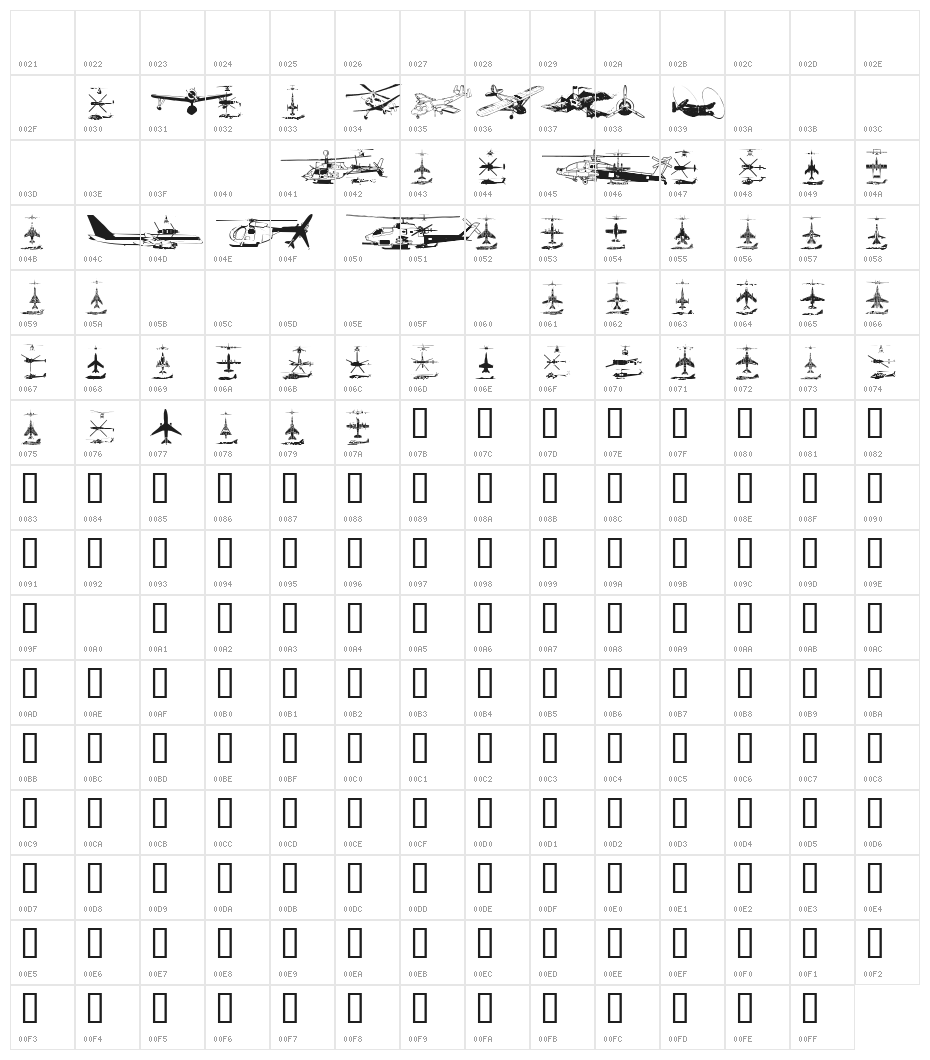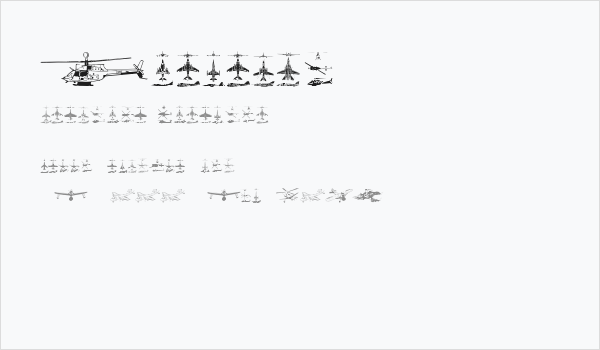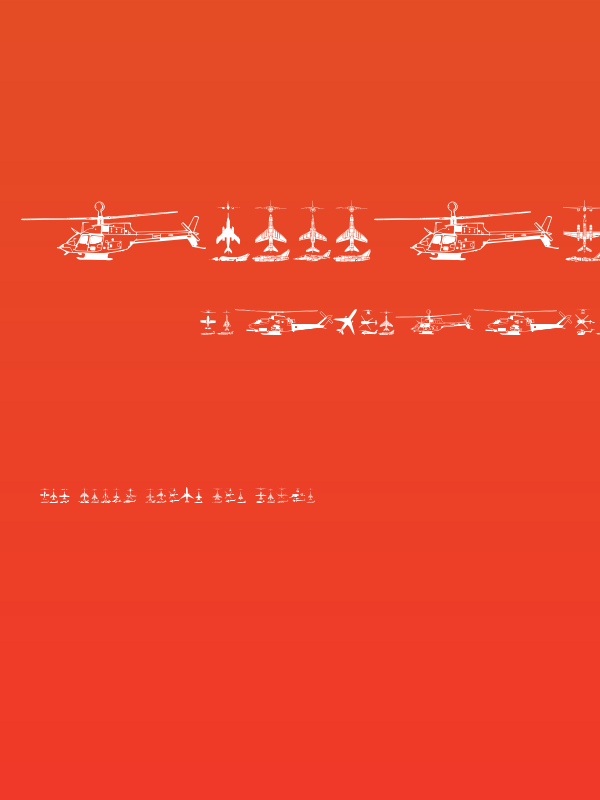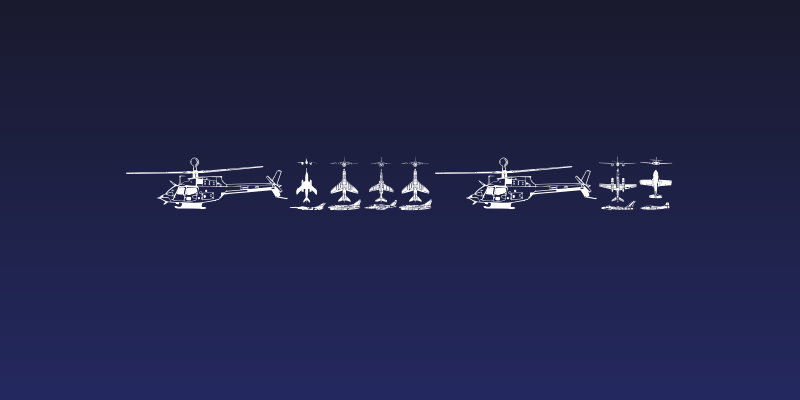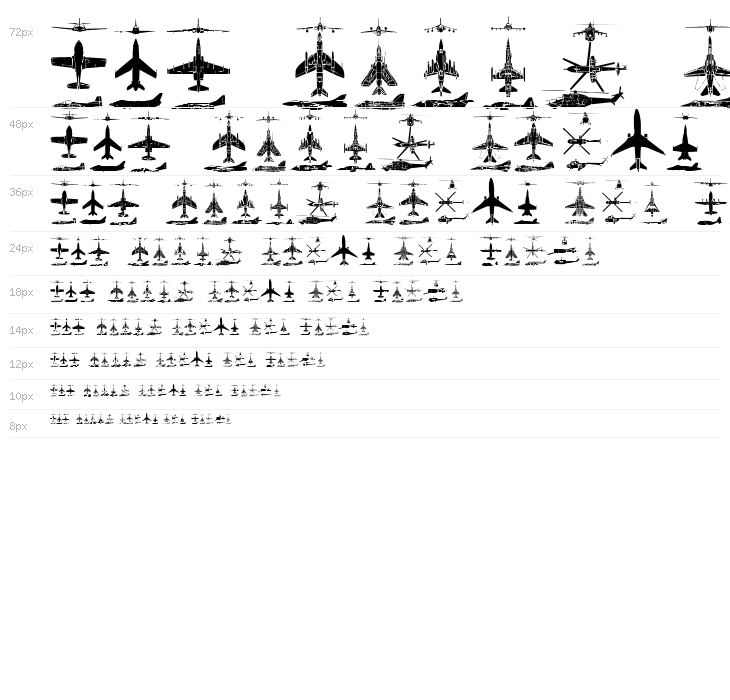
Aircraft Font
| Gesamtstil | Decorative, Thematic, Illustrative |
| Anwendungsfall | Logos, Posters, Themed Headlines, Educational Graphics |
| Vorgeschlagene Projekte | Aviation posters, educational materials, themed event invitations, museum signage, children's books about aircraft, and hobbyist branding. |